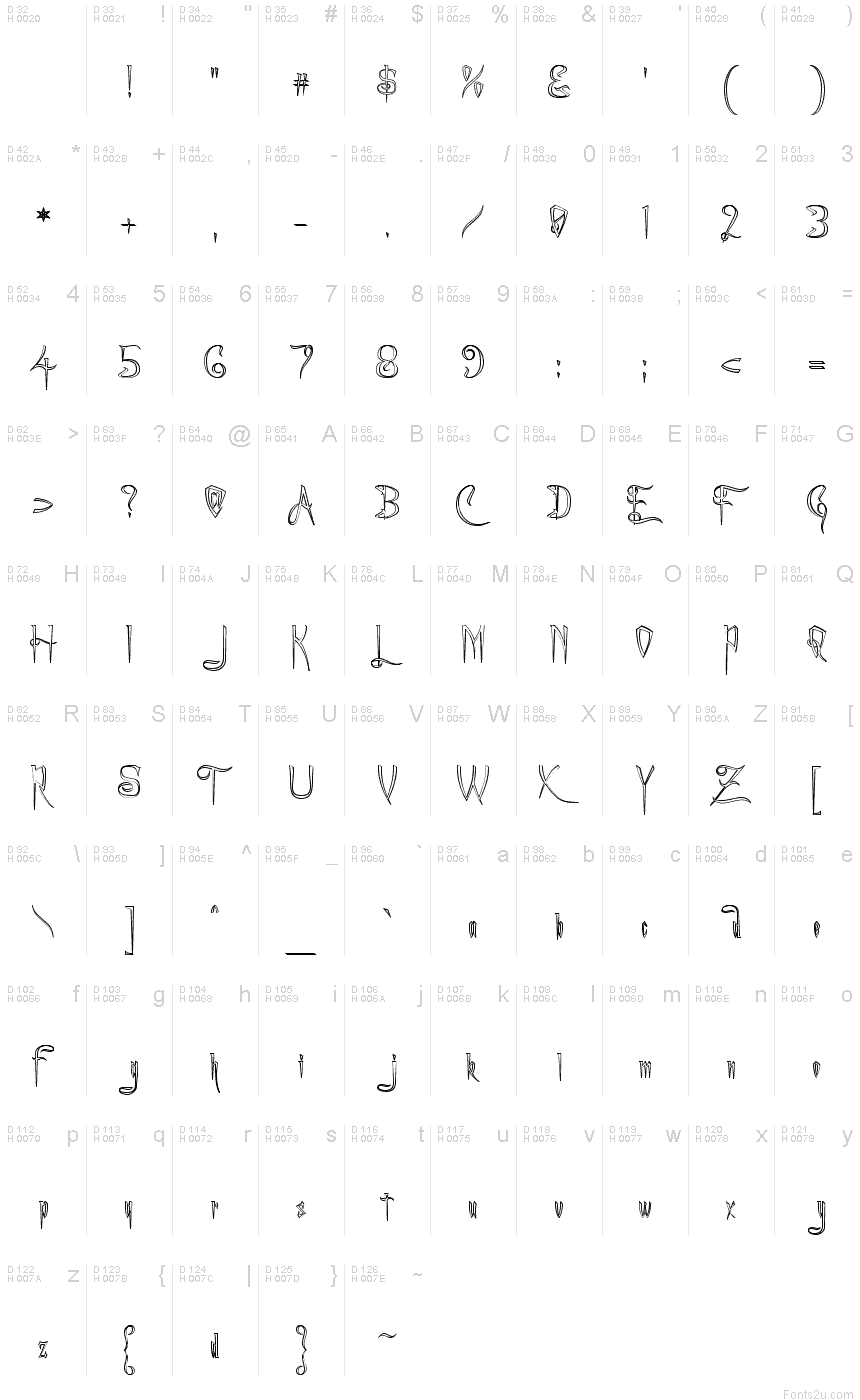
A Charming Font Outline
A Charming Font Outline 由 GeM / A. Höfeld 设计,是一款免费的空心展示字体,能让任何标题瞬间充满故事感。其旋涡状、类似魔法杖的曲线与细长的哥特式尖顶,仿佛是用墨水在陈年羊皮纸上勾勒而成;空心的轮廓线条带来一种轻盈空灵之感,而非沉重的压迫。A Charming Font 家族的这款字体不仅有着出众的装饰美感,更不会让版面显得拥挤。
这款免费的 A Charming Font Outline 字体非常适合奇幻小说封面、魔幻或万圣节主题海报、神秘派对邀请函、游戏或 Cosplay 品牌设计、YouTube 标题卡以及各种充满奇思妙想的标识。开放的笔画设计让您可以自由搭配颜色、渐变或纹理,带来更多魔法氛围。若用于正文,建议搭配简洁的几何无衬线字体,并保持 A Charming Font Outline 的大字号,以确保其精致的细节清晰易读。